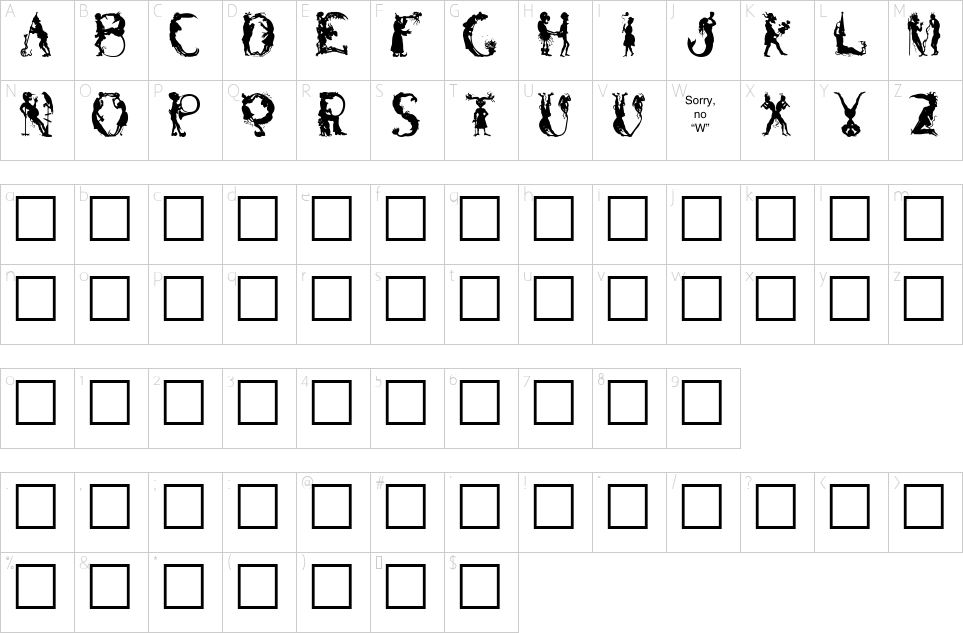
Bizarro é uma fonte casual e versátil criada por David Rakowski, disponível gratuitamente tanto para Windows quanto para Mac. Desde que foi lançada, a fonte tem sido descarregada mais de 19 mil vezes. Suas linhas curvas deslizantes e desbocadas dão ao texto um toque único e desconcertante. Seja em anúncios ou textos legíveis no papel, Bizarro traz um ar inusitado que certamente irá chamar a atenção. Sua facilidade de uso torna-a uma opção ideal tanto para designers profissionais quanto para aqueles iniciantes buscando algo um pouco diferente para personalizar seus trabalhos. Descubra por si mesmo qual papel Bizarro pode desempenhar em suas criações, seja ela um título chamativo ou o texto mais discreto.